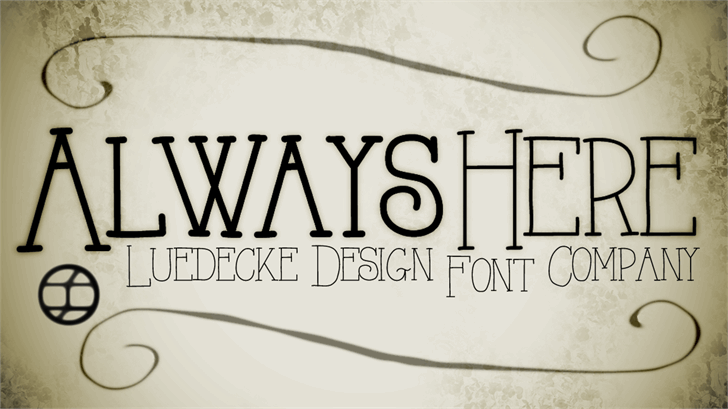
A fonte ‘AlwaysHere’ é uma elegante serif que combina com a cultura brasileira. Suas linhas delicadas e seu design cuidadoso remetem ao nosso rico passado, desde os estilos formais do século XX até as influências modernas da nossa sociedade contemporânea. Especialmente adequada para materiais profissionais como logotipos de empresas, sites corporativos ou embalagens comerciais, a ‘AlwaysHere’ tem um toque suave que é perfeito para texturas sóbrias e escrita clássica. Hamilton, o designer da fonte, não só cumpre padrões de qualidade elevada, como também oferece um serviço atencioso. Para quem deseja explorar as possibilidades comerciais desta bela fonte, Hamilton disponibiliza duas opções: visitar seu site para obter informações sobre preços e condições comerciais, ou doar $50 para ter acesso integral à sua vasta gama de fonts, incluindo ‘AlwaysHere’. Esta combinação de cuidado com os detalhes e apreço por um atendimento eficaz torna a ‘AlwaysHere’ uma escolha inteligente para aqueles buscando elegância na tipografia.